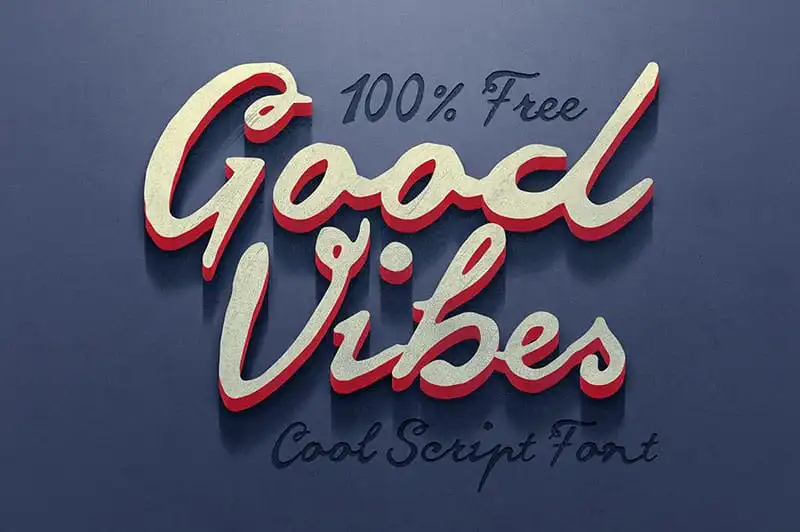
Good Vibes Font – Download Grátis
A Good Vibes Font é uma elegante fonte script que surgiu do trabalho arduo e criativo dos designers Cruzine Design. Esse tipo foi desenvolvido com mão livre, transpirando alegria e vitalidade ao ser usado, transformando cada palavra em um desenho viciante. Se você está procurando por uma fonte script que exibe bom humor e vida, sem dúvida essa é sua escolha ideal. Com seu design fluido e harmonioso, Good Vibes pode revolucionar a maneira como suas mensagens são interpretadas, transmitindo sentimentos positivos em cada letra e espaço entre as palavras. Para designers, escritores e entusiastas de tipos que buscam trazer um toque especial às criações digitais ou impressas, é uma ótima opção. Se você está buscando adicionar um pouco de bom humor e vivacidade a seu trabalho, Good Vibes Font é certamente o tipo perfeito para incluir em sua coleção.